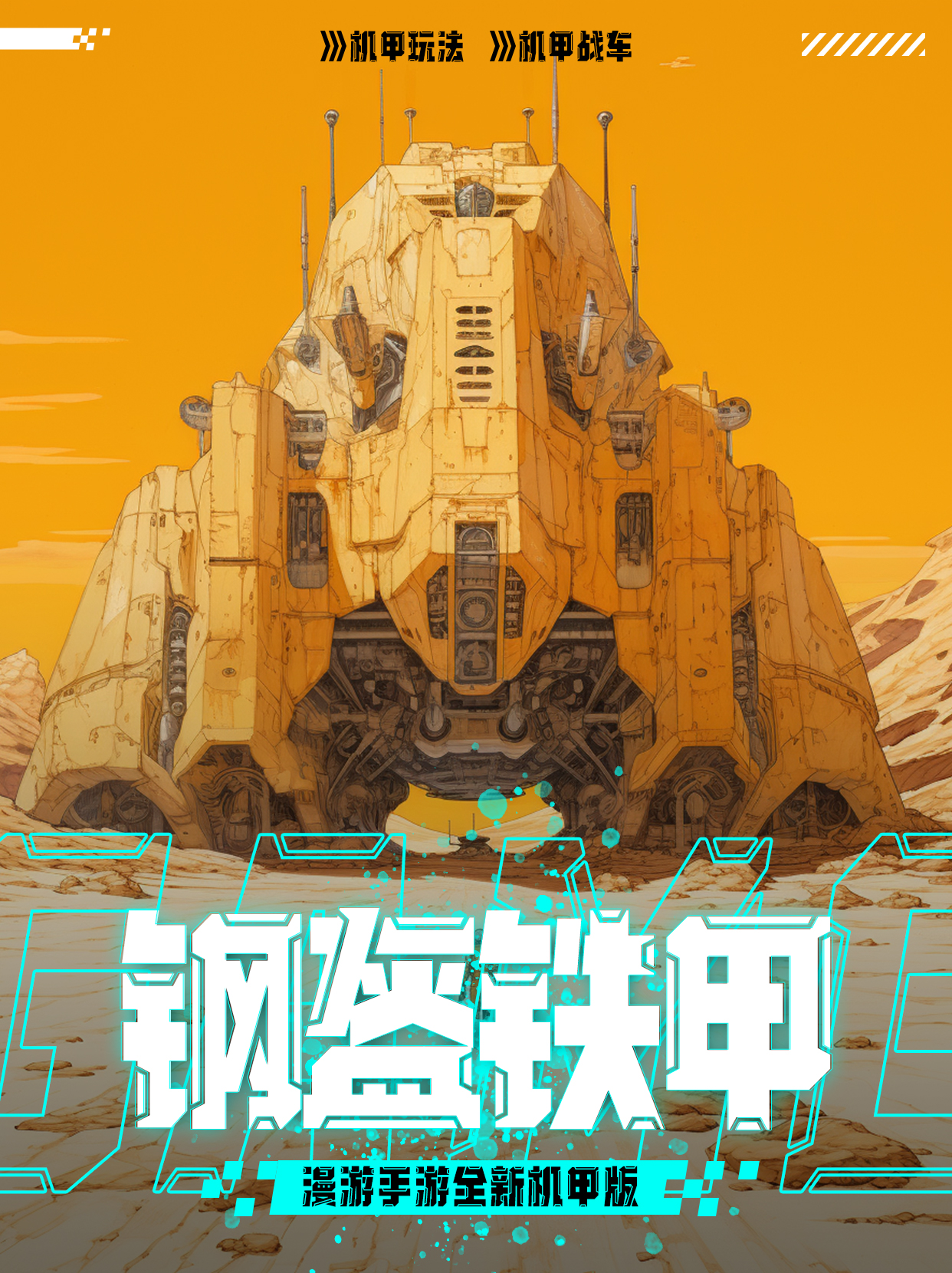
该字体是一款机械感十足的创意字体,笔画转折处采用对角切的方式使字体更加的富有立体感、科技感和现代化的气息。这款字体笔画粗度适中,棱角分明,富有庄重感,字形结构严谨,点画硬朗。更加体现字体的坚毅感和机械现代化的特性。笔画采用切割设计,笔画末端加入斜块装饰元素,浓厚的机械部件感油然而生。整体笔画中通外直,转折硬朗,透露着一种稳重刚毅的力量。